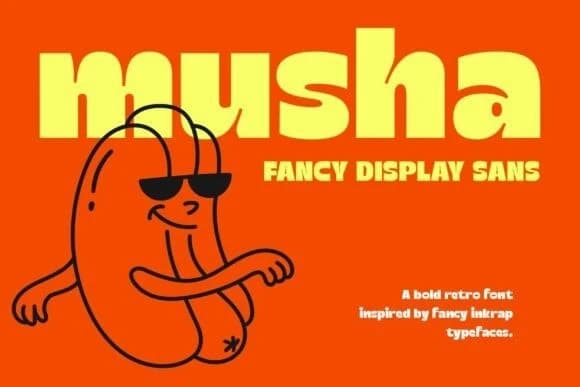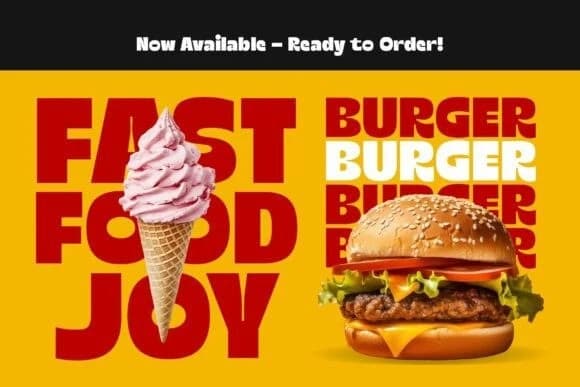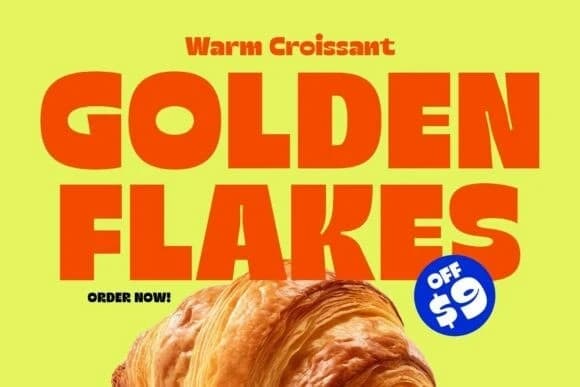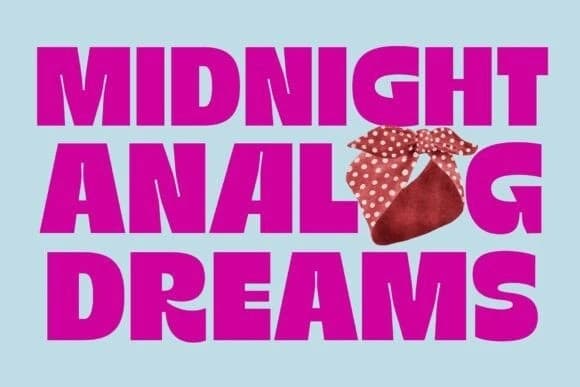
Musha Font
Musha Font, vintage mürekkep damlası tipografisinden, retro ambalaj tasarımlarından ve groovy 70'ler–90'lar görsel kültüründen ilham alan cesur ve eğlenceli bir gösterişli sans yazı tipidir. Kalın eğriler, dolgun iç boşluklar ve beklenmedik iç kesitler ona çok belirgin bir karakter kazandırırken, bü
Musha Font, vintage ink-trap tipografisinden, retro ambalajlardan ve groovy 70'ler–90'lar görsel kültüründen ilham alan cesur ve eğlenceli bir gösterişli sans fontudur. Kalın eğriler, dolgun iç boşluklar ve beklenmedik iç kesimler ona güçlü bir karakter kazandırırken, büyük boyutlarda temiz ve son derece okunabilir kalmasını sağlar.